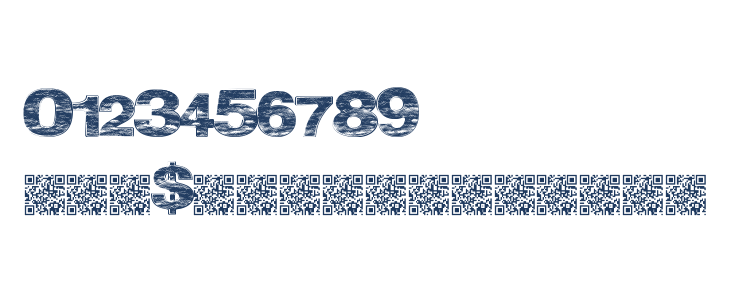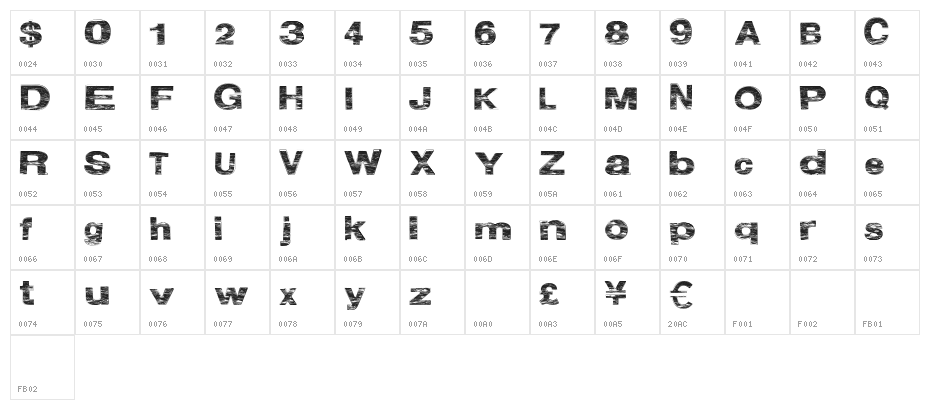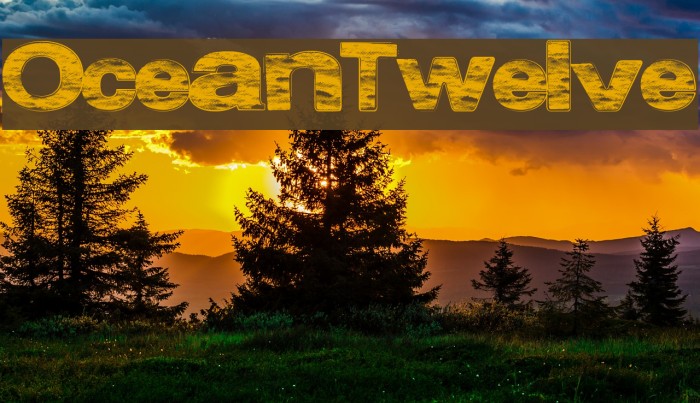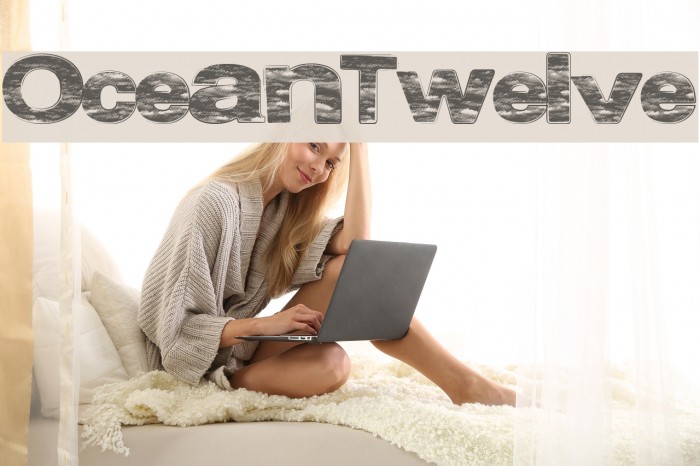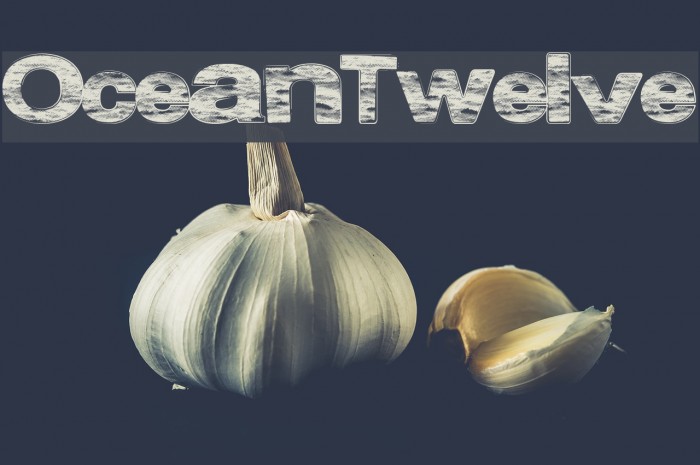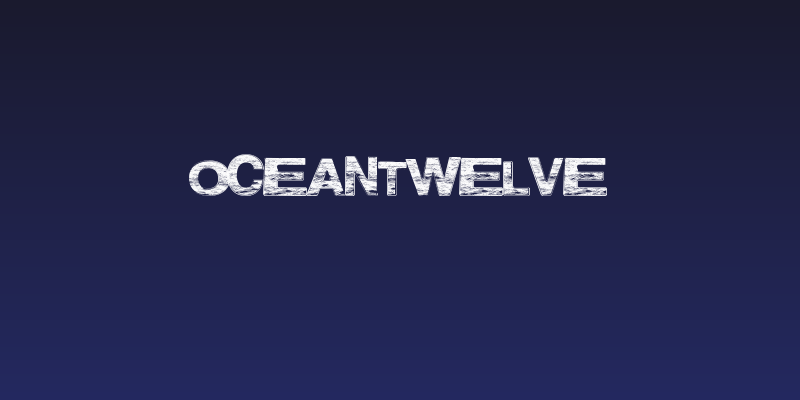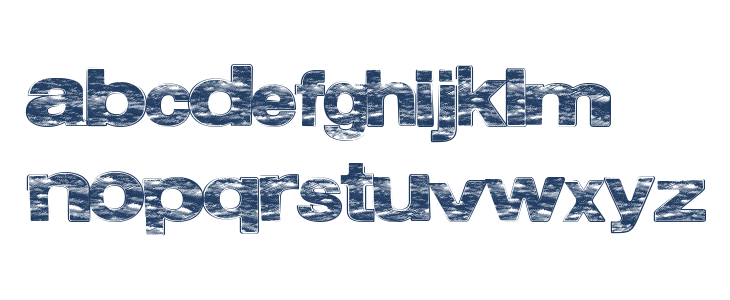
OceanTwelve Font
✎ Distorted Eroded
| Progetti proposti | Ideal for projects requiring a bold statement, such as posters, album covers, or branding materials that aim to convey a sense of toughness or vintage appeal. |